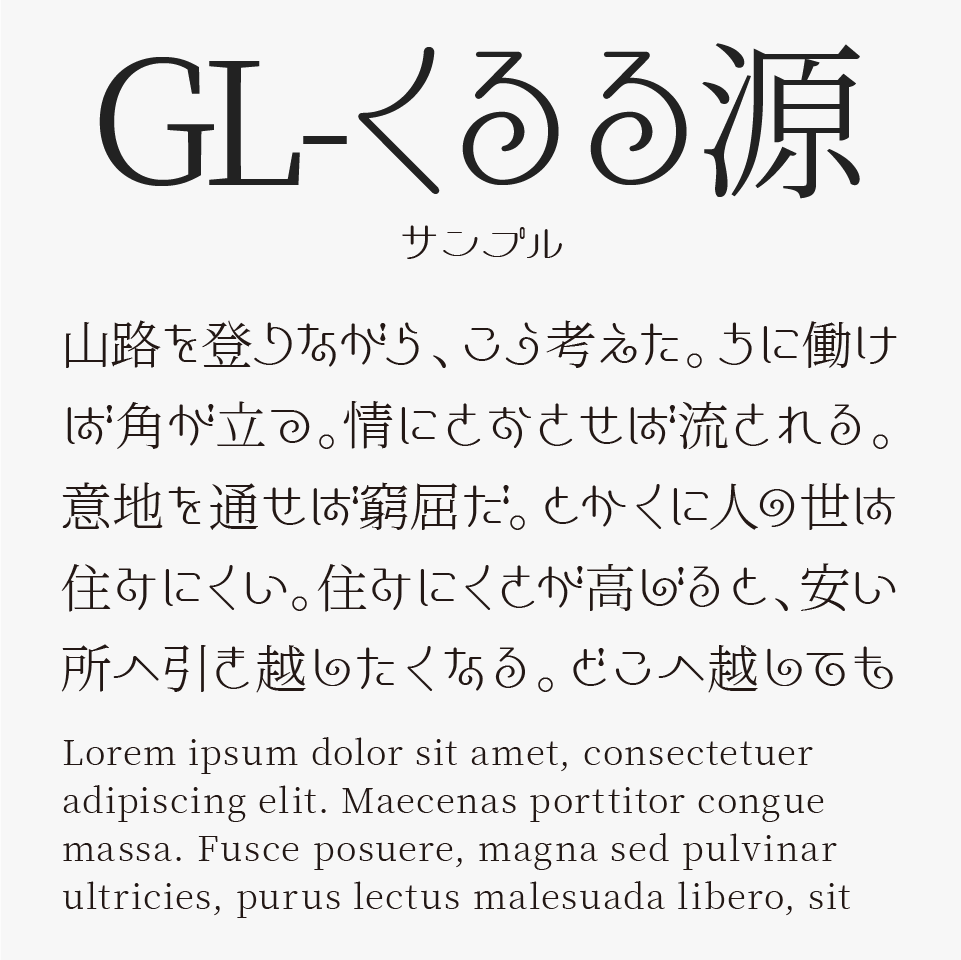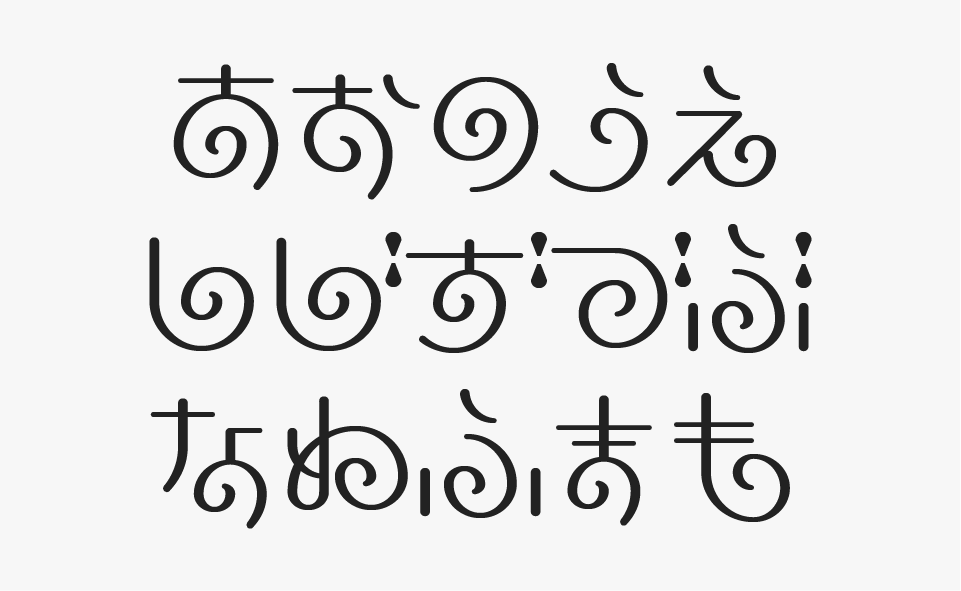
GL-くるる源
GL-くるる源フォントは、細かな渦巻き模様が入ったオリジナルのひらがな・カタカナと、「源ノ明朝」を組み合わせて制作されたデザインフォントです。
見ていると目がクルクル回りそうなぐらい渦巻き模様が、文字に装飾されているユニークでとっても可愛らしいフォントです。
作者の方が「読めなさそうで読める文字」と表現しているように、装飾性が高いにもかかわらず、長文でも意外としっかり読める絶妙なバランス感も魅力のフォントです。すごい!
ぱっと見では異国の文字のようにも見える独特なデザインですが、不思議としっかり読める絶妙なバランスに仕上がっています。さらに、濁点・半濁点には水の雫のような装飾が施されており、幻想的で遊び心のある雰囲気も楽しめるフォントです。